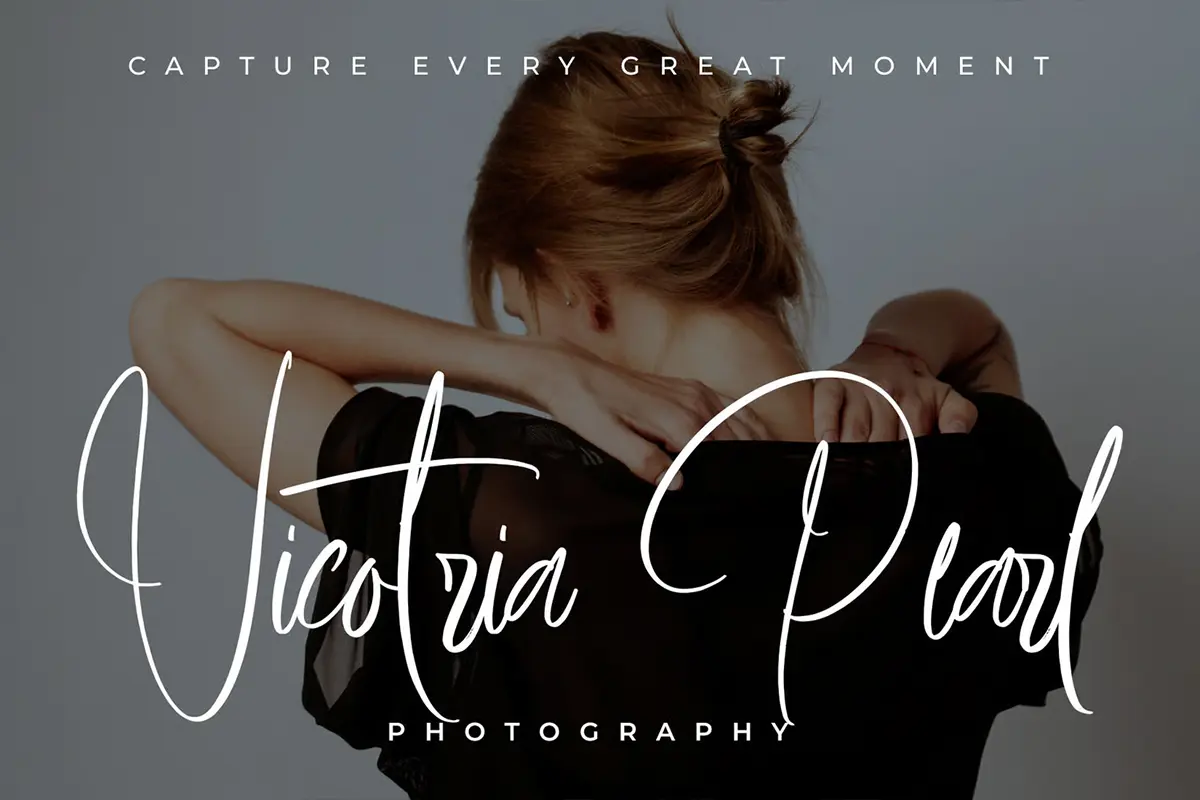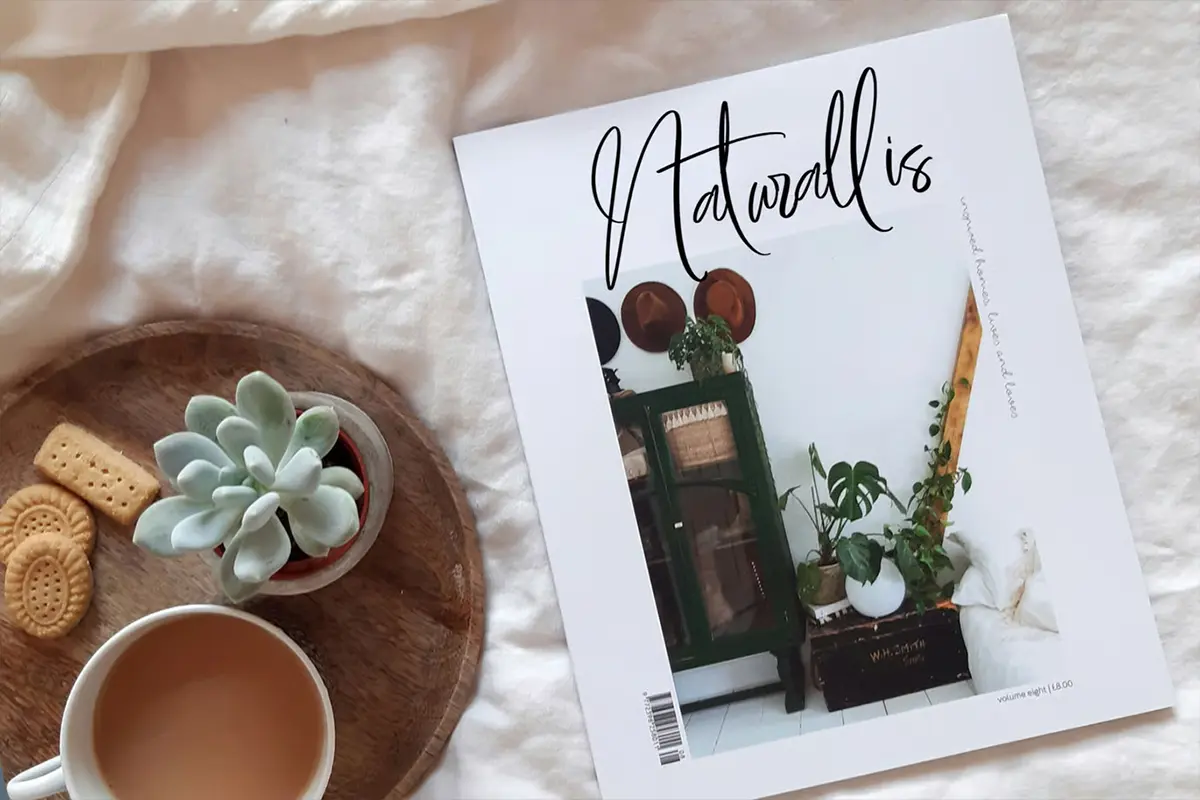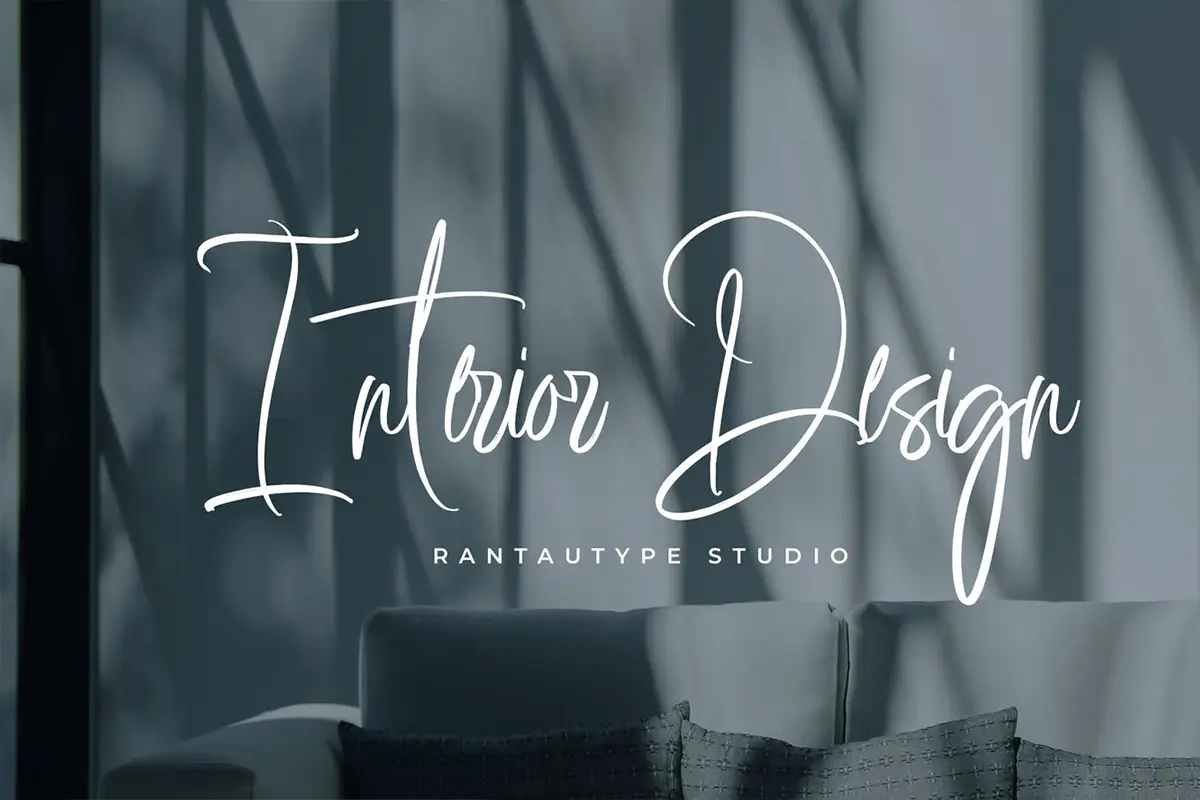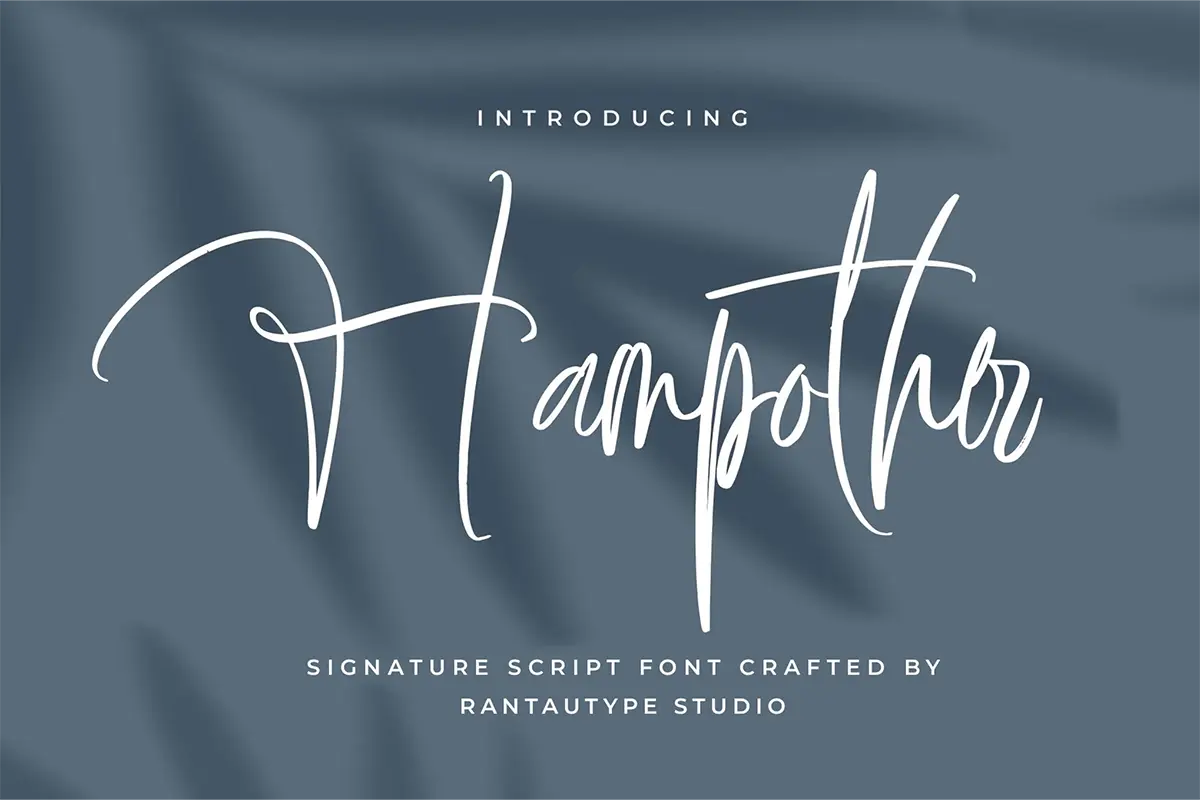
فونت امضایی مدرن و شیک Hampother
فونت Hampother یک فونت امضایی با استایل مدرن و ترند روز است که برای پروژههای خلاقانه و طراحیهای سبک زندگی انتخابی بینقص محسوب میشود. این فونت با خطوط نرم، ظریف و دستنویس، جلوهای لوکس و شخصی به طراحیهای شما میبخشد.
مناسب برای استفاده در طراحی لوگو، عنوانها، کاور مجلات، برندینگ، دعوتنامهها، طراحی مراسم عروسی، پستهای شبکههای اجتماعی، تبلیغات، نقلقولهای چاپی، بستهبندی محصولات، برندهای شرکتی، برچسبها، عکاسی، واترمارکها و هر پروژهای که نیاز به لمس مدرن و خاص دارد.
✨ ویژگیهای فونت Hampother
- شامل حروف استاندارد، اعداد و علائم کاربردی
- دارای آلترنیتها و لیگچرهای زیبا برای تنوع در نوشتار
- پشتیبانی از کاراکترهای چندزبانه
🎯 مناسب برای استفاده در
- طراحی لوگوهای شخصی و برندهای لوکس
- عنوانهای مجلات و کاور کتاب
- دعوتنامههای رسمی و طراحی مراسم
- پستهای شبکههای اجتماعی با سبک مینیمال
- بستهبندی محصولات و برچسبهای شیک
- واترمارکهای عکاسی و طراحیهای تبلیغاتی